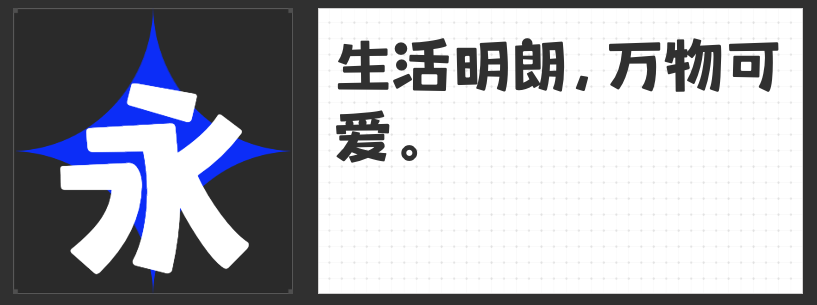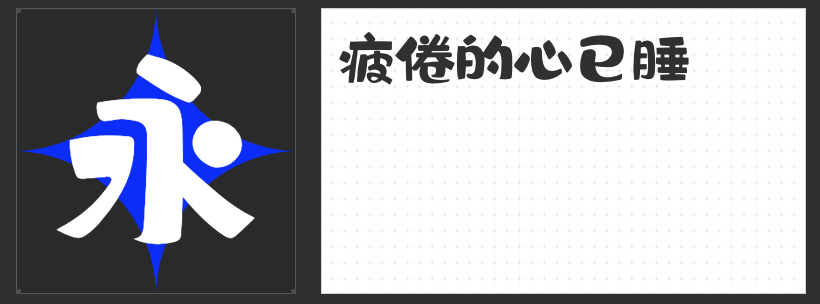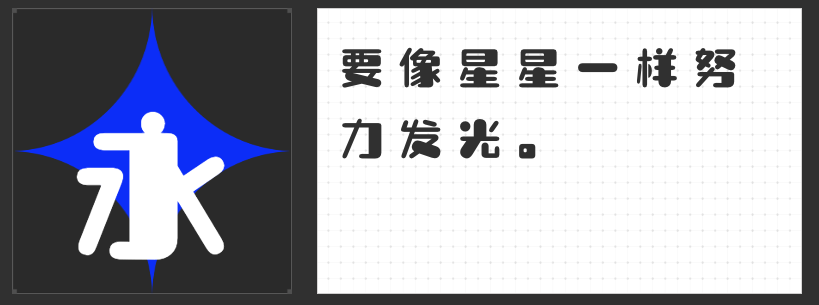
解锁创意新维度:四款风格化卡通字体推荐
在视觉设计领域,卡通字体凭借其独特的个性表达与情感传递能力,成为品牌IP塑造、儿童产品包装、动漫周边开发等场景的核心视觉元素。本文精选四款兼具艺术性与实用性的卡通字体,从自然意象到动态美学,从手写温度到呆萌趣味,为设计师提供多元化的创意解决方案。
一、字恋狂风摇简 粗体
这款字体以“失衡美学”为核心设计理念,通过夸张的笔画倾斜与粗细对比,营造出被风吹拂的动态视觉效果。其手写感来源于对儿童涂鸦的提炼——歪扭的笔画走向、不规则的字体比例,以及部分笔画末端的自然抖动,仿佛记录着书写者随性而真挚的情感。粗体设计强化了字体的存在感,使其在标题、海报等场景中既能传递温暖氛围,又能保持视觉冲击力。
二、喵字芒果体
作为专为芒果农产品打造的定制字体,喵字芒果体将农业的质朴与热带水果的活力完美融合。圆润流畅的笔画模拟芒果饱满的形态,微妙的弧度变化暗喻果肉的多汁质感;字体内嵌的暖黄色调渐变,则呼应了阳光照射下的果皮光泽。这款字体通过视觉语言直接传递产品特性,适用于食品包装、农业品牌标识等需要强化品类认知的设计场景。
三、喵字动漫体
针对动漫产业需求开发的喵字动漫体,在传统标题字框架中注入动态基因。通过笔画末端的弹性收笔、字间微妙的错位排列,以及局部笔画的夸张延伸,营造出“正在运动”的视觉错觉。其设计既保留了汉字的结构平衡,又通过细节处理打破刻板印象,特别适合动漫海报、角色周边等需要强化故事感的场景。
四、励字憨憨简
以“呆萌”为设计关键词的励字憨憨简,通过全圆弧笔画与夸张的部件比例,构建出充满童真的视觉语言。字体中大量使用的圆形元素(如“口”部的正圆处理、“心”底的弧形收笔)与饱满的字形结构,传递出无攻击性的亲和力。其装饰性细节(如笔画末端的微小凸起)进一步强化了手工感,成为儿童绘本、玩具包装等场景的理想选择。
上述四款字体通过差异化的设计策略,将卡通字体的表现力推向新高度。无论是追求动态叙事、自然隐喻,还是情感共鸣、趣味互动,这些字体均能以独特的视觉语言为设计注入灵魂,帮助品牌在同质化竞争中建立差异化记忆点。